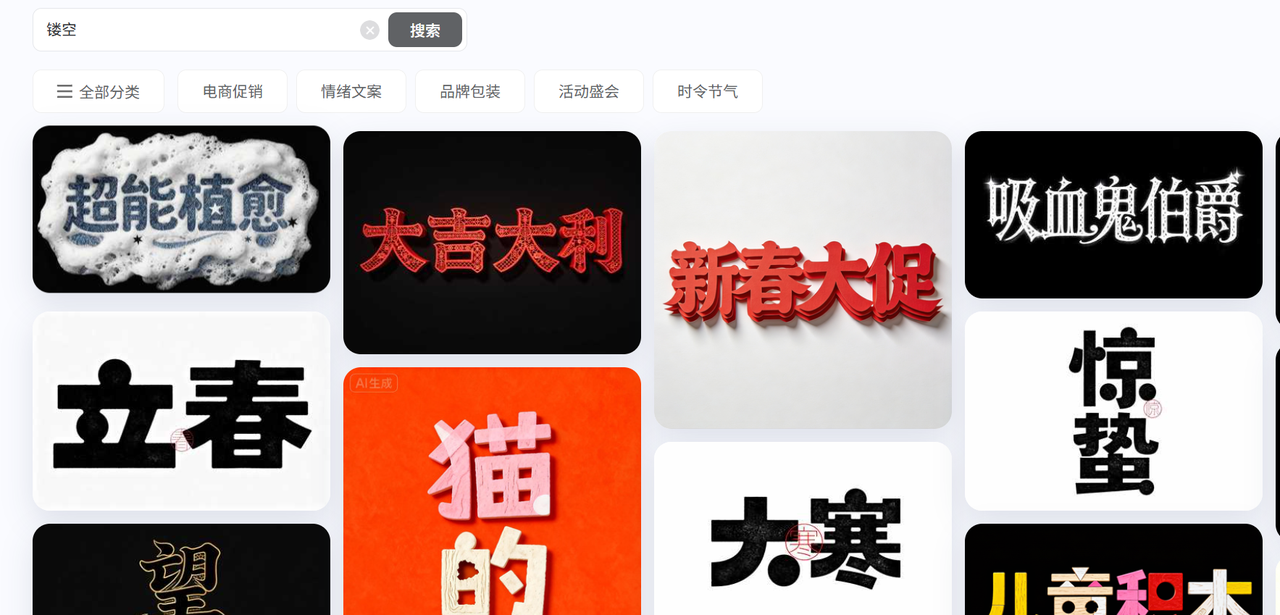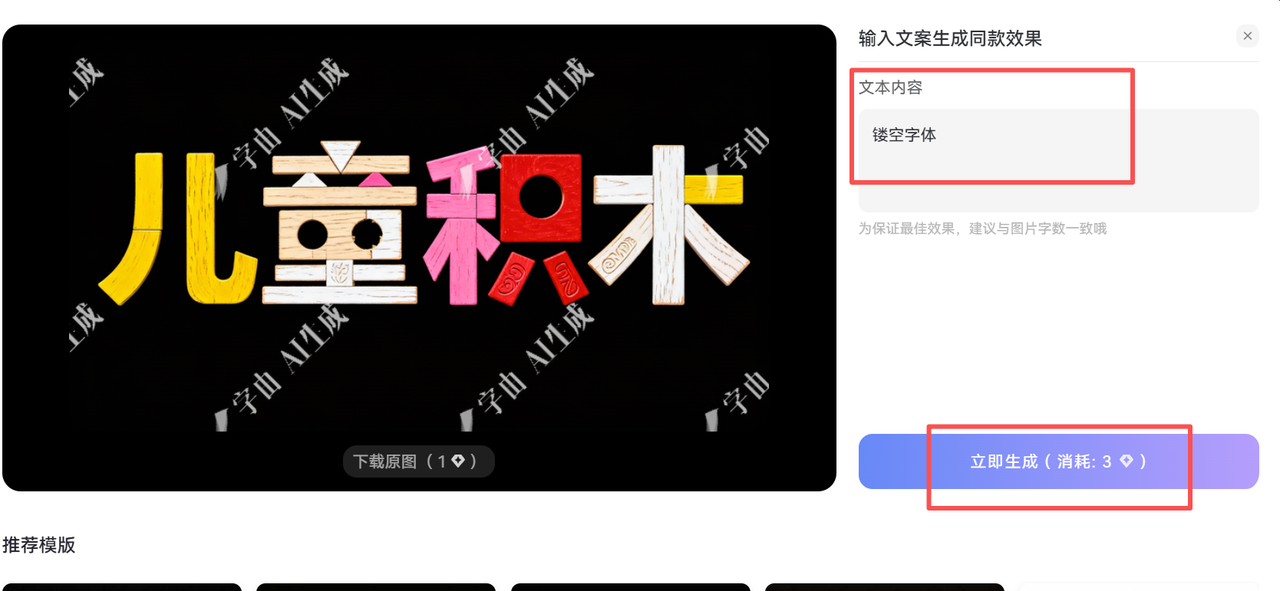
如何下载免费商用镂空字体,教你用 AI 生成
在过去,想要一个特定的镂空字,我得去 Illustrator 里手动描边、路径查找器减去,非常耗时。最近我发现字由 AI 字体功能。
你不再需要下载几百个字体包去试,先选择镂空字体直接输入文字,AI 就能帮你生成同款的的镂空效果。
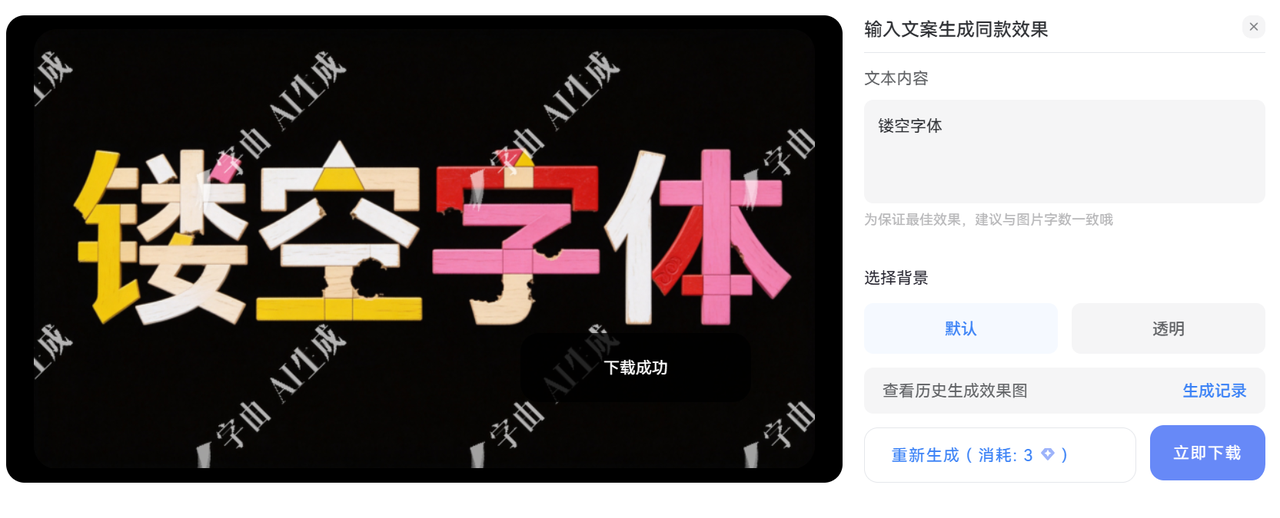
进入页面后,你可以选择“艺术字”功能,输入你的文案,选择带有镂空/空心属性的模板。我个人建议在生成后,尽量将其转曲(Outline)放入你的设计稿中,这样不仅能防止字体丢失,还能进行二次精细化调整。
三、 我常用的几款镂空字体模板
在实际应用中,镂空字并不只有一种风格。根据项目的调性,我通常会从以下几类中挑选,大家可以按需选择。
- 吸血鬼伯爵
这款镂空字体比较适合游戏和万圣节的宣传
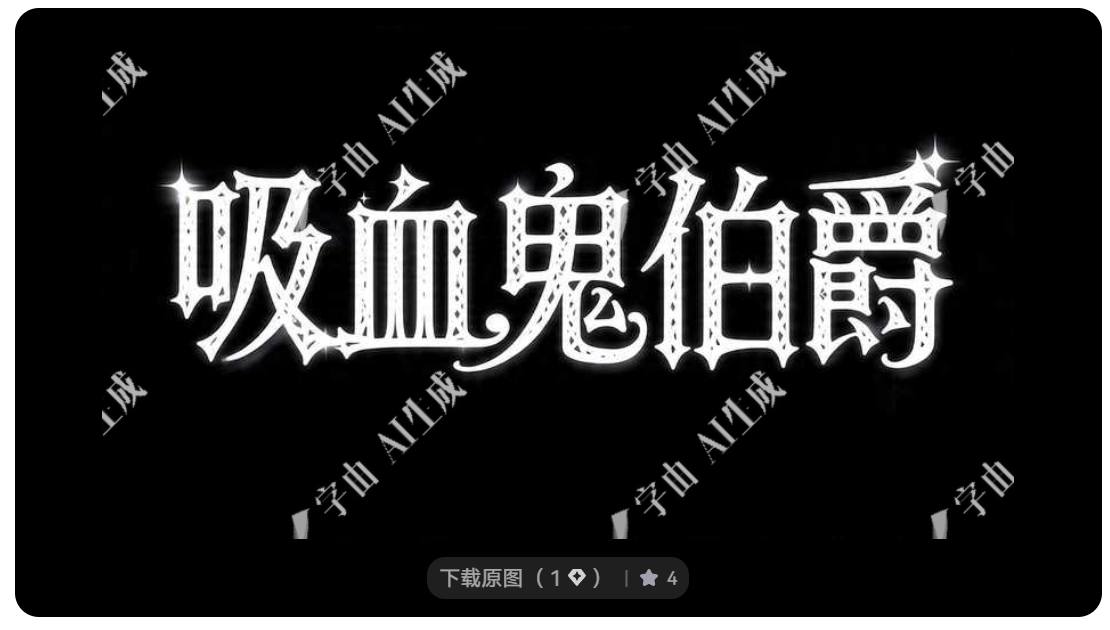
- 顺遂
顺遂模板比较适合海报、红包封面等设计
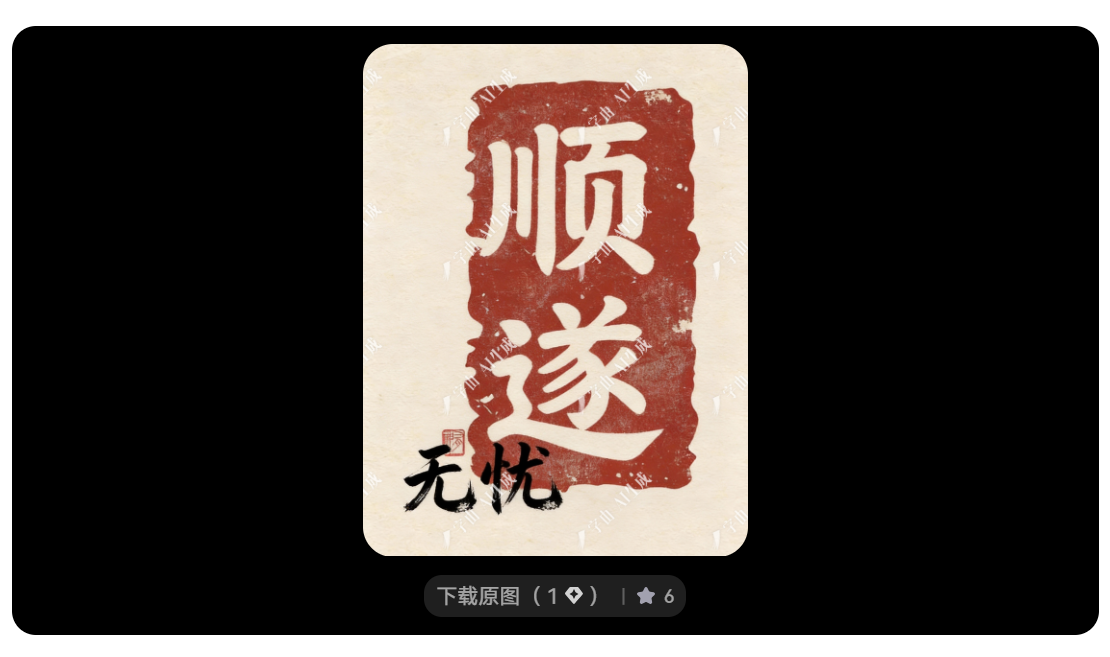
- 星球大战
比较适合一些科技和 AI 相关的场景